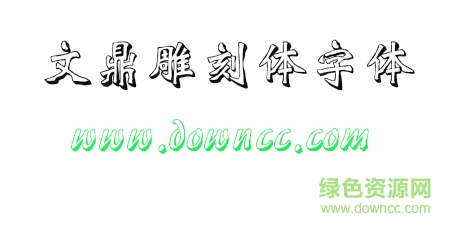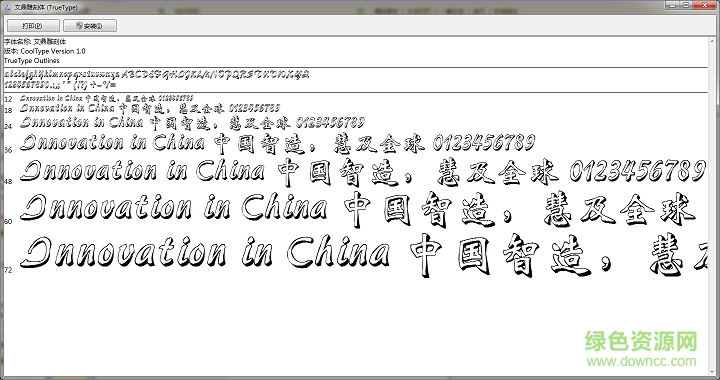
文鼎雕刻體是一款空心簡(jiǎn)體字體,整體效果像雕刻上去一樣的,韻味十足,藝術(shù)創(chuàng)作中比較常見(jiàn),有了這款字體,也能讓你聊天或者辦公時(shí)的字體變得更加具有個(gè)性,感興趣的朋友就快來(lái)本站下載使用吧!
文鼎雕刻體親切、幽雅、柔美和華麗,筆劃粗細(xì)對(duì)比適中,婉轉(zhuǎn)嫵媚,溫順乖巧,看似平淡無(wú)奇,卻能給人以美的感受。適用于個(gè)人用品、化裝品、食品、家居廣告宣傳使用環(huán)境。